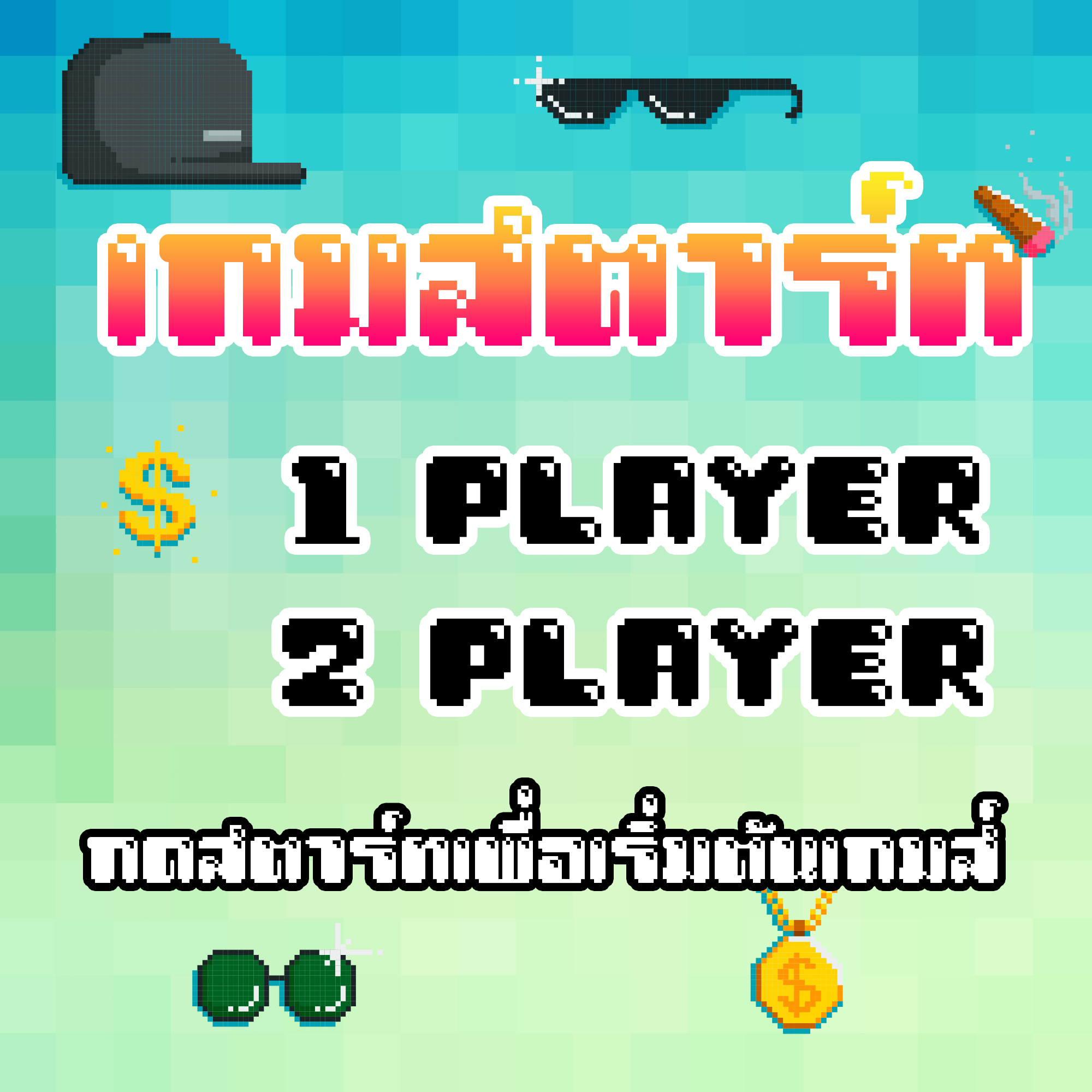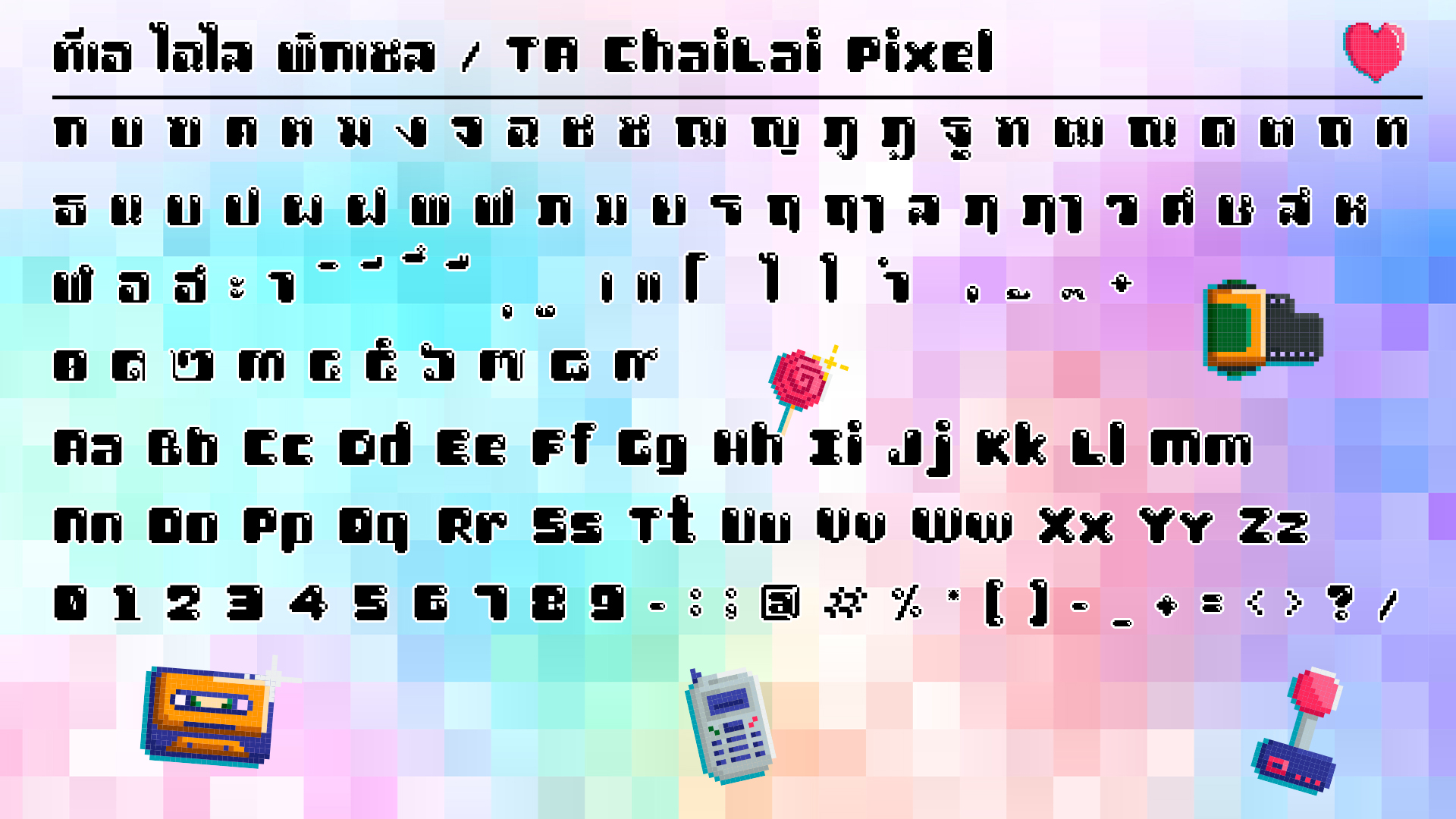
ทีเอ ไฉไล พิกเซล
ทีเอ ไฉไล พิกเซล ฟอนต์
ไอเดียวเริ่มต้นฟอนต์ตัวนี้มาจากไปเห็นฟอนต์แนวไฮไลต์พิกเซลของต่างชาติมาแล้วชอบ
เลยอยากทำฟอนต์แนวนี้เป็นภาษาไทยบ้าง ก็เลยไปขึ้นแบบฟอนต์จากเว็บ www.fontstruct.com
แล้วเอามาปรับรายละเอีียดในฟอนต์แล็บอีกทีครับ